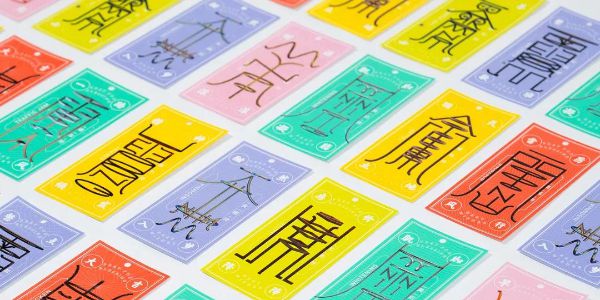
来自8个国家的14位设计师的字体设计分享
什么是马拉松精神
想要成为一个优秀的马拉松选手,最重要的事情就是必须具备能够经受精神上和肉体上各种痛苦的忍耐力和能够控制自己的自制力,并且经常表现出对竞争的新鲜热情,保持着不断地向自己的最终目标努力的情绪。一个优秀的字体设计师也如此。
这里有来自8个国家的14位设计师,他们都擅长视觉游戏,更热爱字体设计,那么14人就来一场游戏,不是比赛看谁最棒,而是把对字体的热情与温度传递给下一位设计师,这样游戏应该是文字马拉松~希望这种文字文化与智慧围绕着您!
仲条正义
Japan
一位出色的字体设计师应该是怎么样的?给字体设计师一些建议?
我认为一名出色的图形设计师是由时代决定的,他应该对时代敏感,一名出色的字体设计师他们应该是喜欢看字和写字的人。不管走到哪里都对字体保持洞察力,例如在街上的时候,会注意到一些书籍或杂志上所使用字体,就算是在电视机旁边都能认出出色的字体设计。
Hiroto Nagai
atooshi
Japan
您了解的中国是怎么样的?可以用一款字体来形容中国吗?
我想用两个词来形容我了解的中国:“历史”、“繁华”。这在很早之前就存在了,中国的现代设计也有类似的特点。比如说,多层次的修饰,生动的色彩运用。用字体举个例子吧,我觉得Kocho这款字体最能代表中国,Kocho是一种深奥微妙的、强大的字体,和中国一样。
▲Sanuki Takamatsu Chihama’s Ajinori and Yakinori
Takasuke Onishi
direction Q
Japan
您认为字体设计师的幸福感来自哪里?
在我看来,字体是一种人类的声音。当我能从一个字体里听到声音时,这就是一个成功的字体。
▲Tohl Narita Project
Yunlong Li
Would design
China
您认为中文字库里最美丽的字体是哪一款?为什么?
我比较欣赏的一款字体是秉楠圆宋,这款字体的设计师余秉楠把传统宋体笔划末端的“角”用“圆”重新设计,摆脱了传统宋体字的机械感。在保留传统宋体字端庄优雅、结构严谨的特征的同时创造了圆润亲和的字体感受,富有人文精神。它对于印刷排版和荧幕显示都很友好,作为正文字体灰度均匀,阅读起来也比较舒适。另外秉楠圆宋的拉丁字母部分也很出色。
▲Chinese New Year of Rooster Gift Box
Ronn Chen
HereThere Studio
Taiwan
一些著名的品牌大多数拥有经典的字体设计,作为设计师怎样理解“经典字体设计”?
中文字体设计令人印象深刻的有时候是书法字体的运用,像人民日报、中国银行、鄂尔多斯。中文是象形文字的基础,书法风格变化大,给设计带来很多创意元素,可以与英文或者图形结合,创造出崭新有趣的面貌。
▲Time to Let the World Know
Yu-Shu Chien
Taiwan
台湾的设计一向拥有自己的风格,您喜欢用什么字型(字体)?为什么?
我更偏向国际字体风格,这种风格对我影响很大。我设计的作品也是这种风格:没有过多修饰,更注重实用性和合理性。
▲Xin
Adrian Panadero
And A Half Branding and Design Studio
Philippines
可以谈谈您计算机里的字库吗?
在过去几年,我见证了各种字体兴起和衰落。准确来说,我自己没有计算机,我是用的公司的计算机。我计算机里的字库是Mac's Font。
▲Milk Trade
Driv Loo
L I E
Malaysia
您是如何看待西文字体和中文字体在发展上的区别?
因为汉语是语标式语言,英语是表音式语言,所以,在我看来,中文字体比西文字体更感性,更具有象征意义,这在人们的文化和思维模式上也有所体现。
▲Kaiju Company
Fan Cao
China
你最喜欢什么样的汉字?它美在哪里?
我特别喜爱东巴文:一种兼具表意和表音的图画象形文字。“人则人,物则物”,既有所传递又有所描绘,生动又幽默。最让我所着迷的是文字的规则,不同性格的笔划在一种规则下排列组合,并达到视觉上的和谐统一,重量和结构与规则共生。
▲Open Minded Book Show
Chae Byung-rok
South Korea
在世界各地很多机场、地铁站等场合都看到汉字,你希望您的城市可用一款什么字体来代表中国?
当我创作一些有力量的图像作品时,我会使用超粗黑简体。我查阅了很多中国的古籍,研究印刷体作为一个图形和字体,扮演着怎样的角色。印刷和手写两种形式的结合让字体的表达方式更丰富,也是中国字体的力量所在。
▲Wondo (Typeface Original Drawing), Story of the Two Designers
▲2016 New Year Greeting Card
Kjell Ekhorn
Non-Format
Norway
请谈谈你对中国的理解。
1989年,我首次来到中国大陆,透过上海外滩的江面远眺,只见到一个很普通的工业区。如今,仅过去几十年,老实说,它已变成一个风景如画的城市,让人难以置信。
▲Station 1, 2 & 3
Jon Forss
Non-Format
UK
可以用一款字体来形容中国吗?
能看到这么多出自中国的字体和平面设计,我感觉很兴奋。如果真要选出一种代表中国的字体,我会从字体的根源出发,选择中国书法。中国书法是一种很漂亮的象形文字,我对其充满敬畏。
▲Station 1, 2 & 3
Hong Ko
KL&K Design
Hong Kong
你认为中文字体和西文字体的区别在哪里?
西文趋近符号,笔划简洁,在设计上要将它转变成图像比较困难,要经过多重的变化与编排才能完成一幅精致的图像。东方文字相反,笔划多,整体文字方正,让人有比较重的感觉,所以在设计时我们尽量将它图像化。东方与西方各有优势,设计时会互补来达到平衡。
Nick B.Smith
Spy Studio
UK
我们在机场、地铁站等场合都看到汉字,您希望您的城市可用一款什么字体来代表中国?
由于常年生活在英国,我能见到中文字体的机会还是很有限的。但时不时,我还是能从一些标识和包装上看到汉字,但多半是宋体的。所以对我来说,宋体这一传统的中文字体更能代表中国。
Roberto Sensi
Bocanegra Studio
Italy
可以分享一下您计算机里的字库吗?你用得最多的是什么字体?
Bocanegra工作室通常只使用几种有限的字体。整个项目做下来,我们也许不会超过8-10种。受现代主义风格的影响,我们更倾向于使用sans-serif字体家族,最主要是Helvetica和Futura。当然我们也喜欢使用Serif字体家族,比如说Caslon和Baskerville。总之,我更喜欢使用有各种字重的字体,因为这种字体能让文本用各种声音说话,但不破坏其连续性。